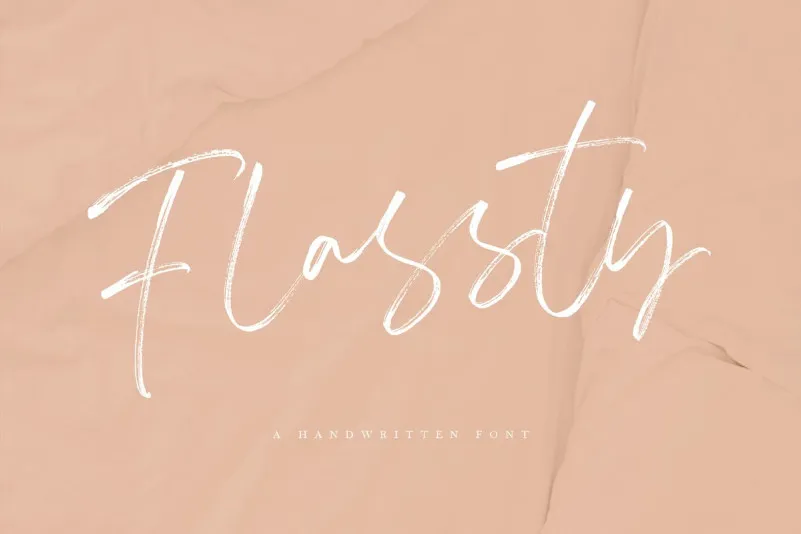
Flassty Handwritten Font
Aqui está uma descrição em português para a página de download da font ‘Flassty Handwritten Font’, mantendo os requisitos fornecidos: O Flassty é uma fonte escrita à mão que captura perfeitamente o estilo elegante e sofisticado do traçado. Com um tom mais natural, ele se ajusta perfeitamente para qualquer projeto que precisa de um toque autêntico de letra escrita a mão. A fonte tem uma textura bem definida, feita ao escrever diretamente no papel com um pincel tipo forte, garantindo uma consistência na qualidade e na sensação feminina dos traços. Flassty é especialmente apropriado para quem deseja adicionar um toque de elegância à sua obra, seja em artigos digitais ou impressos. Ele inclui ligaturas que permitem alterar letras menuscas semelhantes a outros caracteres disponíveis, o que dá ao projeto uma sensação de liberdade criativa. Além disso, oferece alternativas para letras menúsculas, permitindo um ajuste ainda mais personalizado ao seu gosto. Além da elegância e sofisticação, Flassty também possui uma textura embutida em todas as suas linhas e espaçamentos, garantindo que seja fácil usar em qualquer tipo de documento. Seja para criações digitais ou impressos, você encontrará no Flassty tudo o que precisa para dar um toque único a seu trabalho.